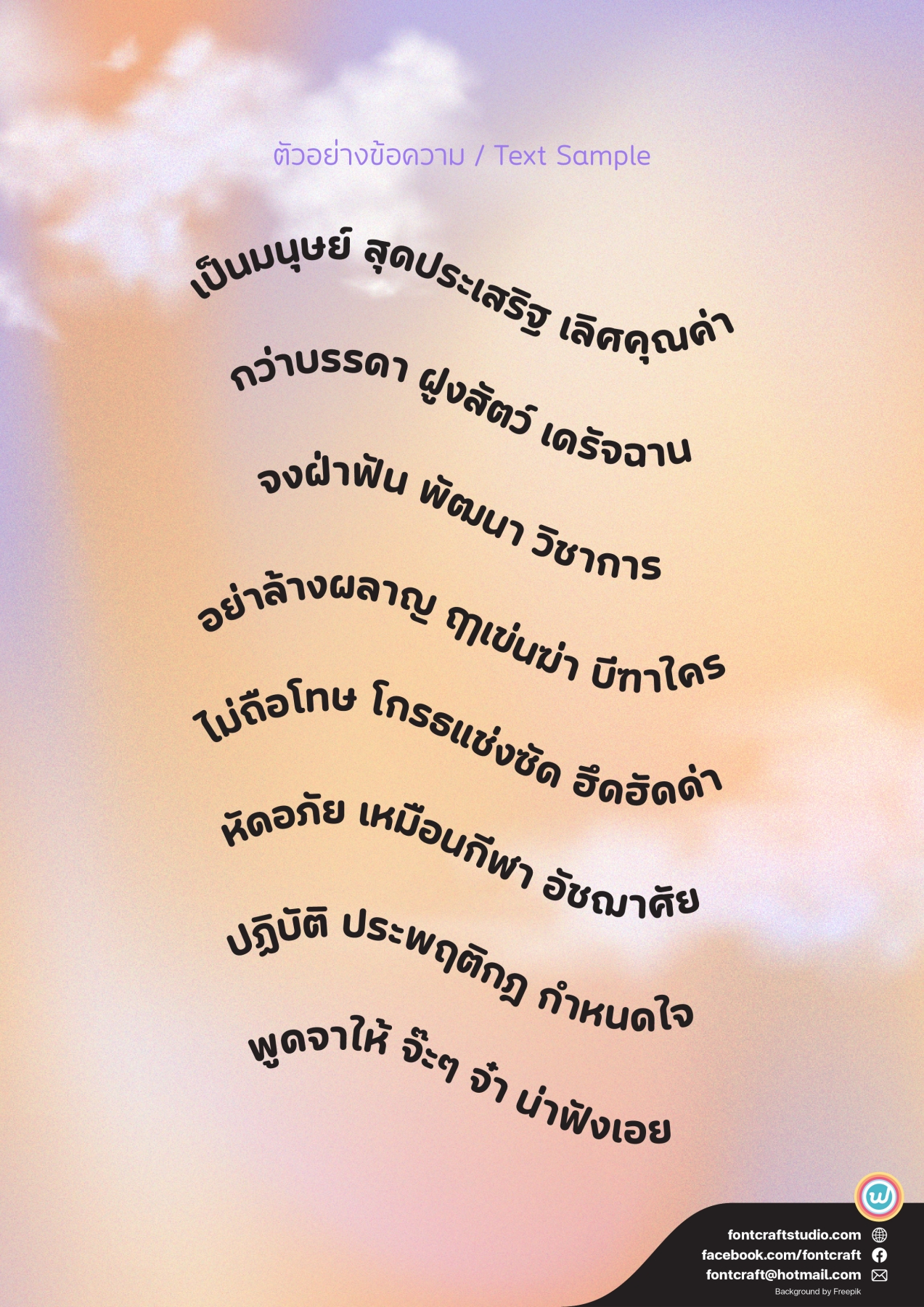
เอฟซี อิสระ ราวด์ (FC Issara Rounded)
ฟอนต์เอฟซี อิสระ ราวด์ (FC Issara Rounded)
ตัวที่จะมาเติมเต็มความเป็นมิตรให้กับเอฟซี อิสระ
ฟอนต์เอฟซี อิสระ ราวด์ (FC Issara Rounded)
ปลายมน เป็นมิตร และอิสระ
ชักชวน เชิญชวน ให้ผู้ชมได้เปิดใจอิสระ สู่แบบทางเลือกปลายมนที่พร้อมผูกมิตรกับทุกคน เหมาะกับการสื่อสารที่ต้องการให้ดูเหมือนจะจริงจัง ที่แฝงความจริงใจ และไว้วางใจได้เสมอ
มาพร้อมน้ำหนักให้เลือกใช้ถึง 5 ระดับ 10 สไตล์ และปรับได้โดยละเอียดผ่าน Variable Font